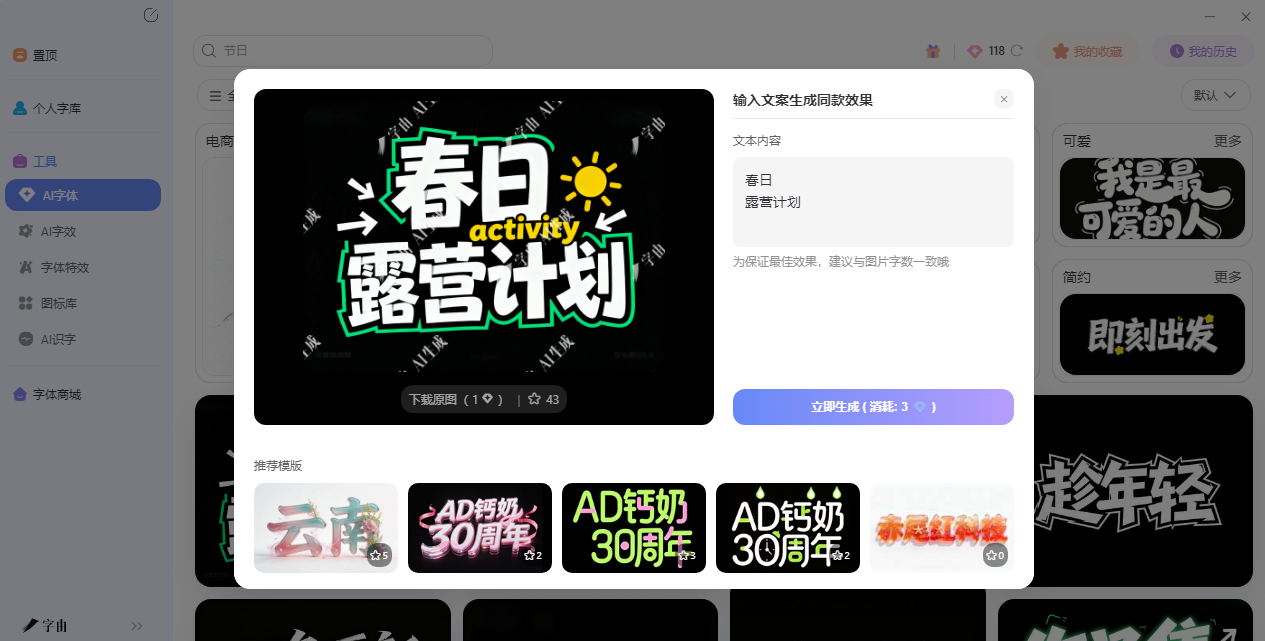
在线艺术字转换器,不用PS也能做标题
做海报封面、发社交媒体配图、设计 Logo 标题的时候,你是不是也想过:要是能有一款工具,输入文字就能直接变成艺术字,不用打开 PS 调半天图层样式就好了?现在网上有不少这样的艺术字转换器,输入文字选个模板或者样式,几秒钟就能出效果。今天整理了 5 个不同方向的转换工具,从 AI 一键生成艺术字图片,到复制粘贴的花体字,再到形状填充和 ASCII 字符画,覆盖了各种玩法,感兴趣的话就往下接着看吧!
字由是目前国内设计师用得最多的字体管理与 AI 字体平台之一,它的 AI 字体功能本质上就是一个艺术字转换器——不需要你懂设计,选个模板改几个字就能出图。
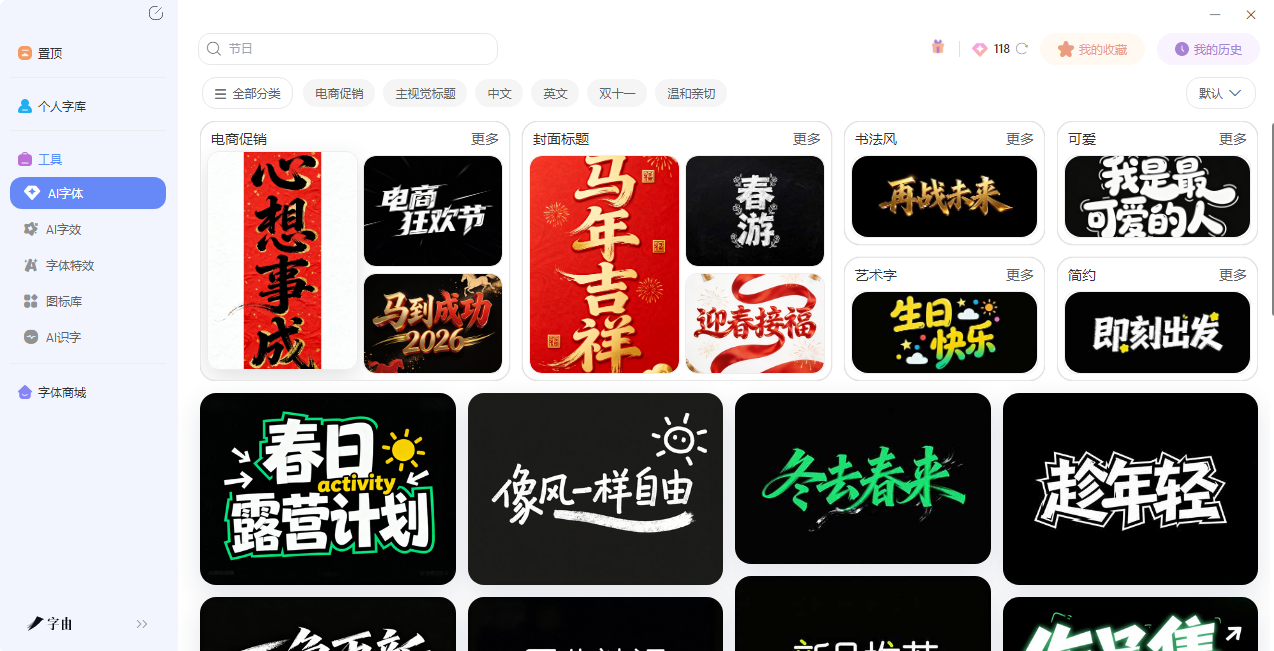
打开字由客户端,在“AI 工具”里找到 AI 字体入口。里面有多种字体特效模板。具体操作也很简单,很容易上手:首选可以根据自己的需求先筛选场景(比如要做电商促销海报,就选“电商促销”分类),找到喜欢的模板点“做同款”,在右侧输入自己的文案,点“立即生成”,等待 10 秒左右,系统就会生成一张带特效的艺术字图片。
生成后可以下载 PNG 格式,背景默认透明,直接拖进 PS、Canva、剪映里就能用。字由每天登录会赠送免费算力,日常生成完全够用。如果你做海报、封面、Banner 时经常卡在“标题字和海报画面不符”这一步,字由的 AI 字体比手动调参数快太多了。
2、Font Generator
第二个网站是一个 Font Generator,截图显示它提供了 200 多种独特的字体样式,主打“生成后复制粘贴”的使用方式。输入文字后,系统会生成各种花体、粗体、斜体、哥特体、气泡体等样式,每种样式旁边都有一个复制按钮。复制后的文字可以直接粘贴到 Instagram、TikTok、Roblox、微信等任何支持文本输入的地方。这个工具还提供了移动端 App(iOS 和 Android),方便在手机上直接生成花体字。
和生成图片的工具不同,这类生成器输出的是 Unicode 字符,所以不挑平台,任何设备都能正常显示。如果你只是想发一条花体字朋友圈,或者给游戏昵称加点个性,这个 Font Generator 比打开 PS 做图方便太多。
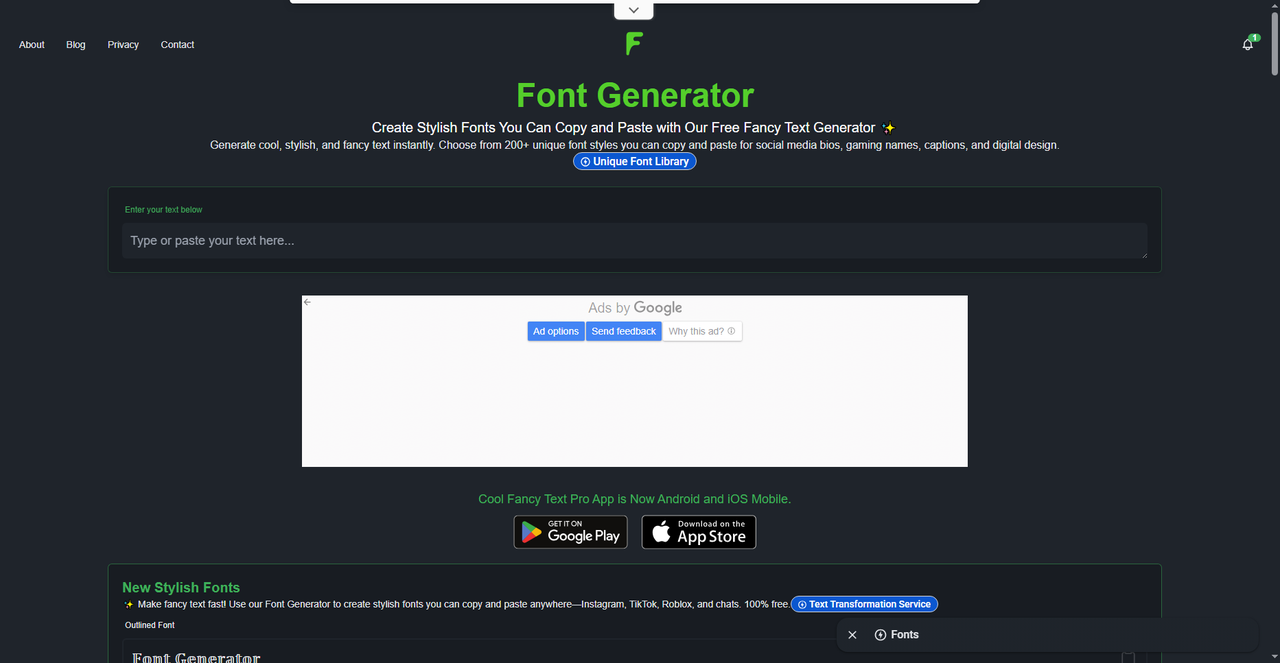
3、在线艺术字生成器
第三个是一个中文的在线艺术字生成器。它的特点是支持丰富的参数调节:可以选字体(比如“凉如三月”这种艺术字体),调文字颜色、背景颜色、字体大小、旋转角度、图片尺寸、字体投影、边距等。输入文字后,点击“生成”就能看到预览效果,然后下载图片。这个工具适合那些“对花体字不满意,想要更自由控制”的用户——你可以自己搭配颜色和背景,让艺术字更贴合海报的整体风格。相比纯花体字生成器,它多了一些设计自由度,又比 PS 简单很多。如果你需要的不是简单的 Unicode 花体字,而是一张真正可以放在海报里的艺术字图片,这个生成器值得一试。
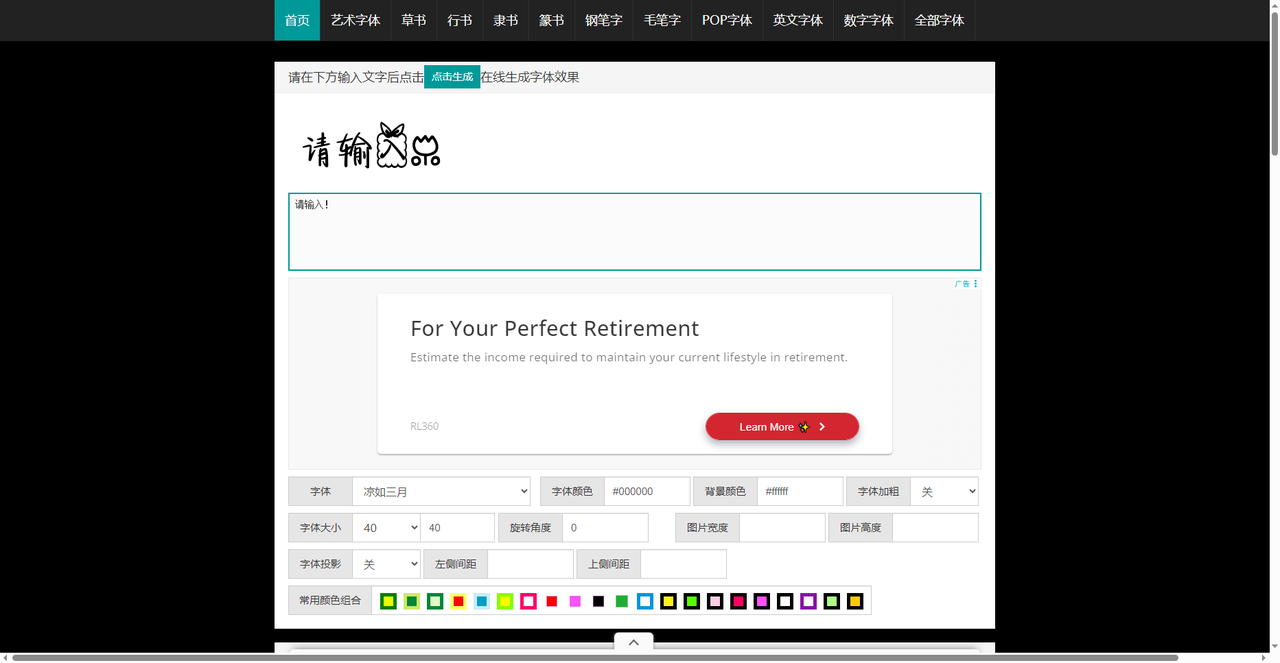
4、Wordificator
第四个工具叫 Wordificator,一个创意形状文字艺术生成器。它的玩法很特别:你选择一个形状(心形、圆形、动物轮廓等,也可以上传自己的图片),然后输入一组文字,系统会把文字按照形状的轮廓排列填充,生成一张形状文字海报。截图里展示的是心形填充效果,文字有不同的大小层级——用 * 开头的行会变成“Featured”(突出显示的大字),其他行作为小字填充周围。你还可以设置字体、颜色方案、背景色、字体大小等参数。生成后可以导出 2048×2048 的 PNG 图片。Wordificator 适合做活动海报、T 恤图案、社交媒体封面等需要“把文字排成特定形状”的场景。比如你要做一张“LOVE”主题的情人节海报,用 Wordificator 选心形,输入 LOVE、SMILE、BE HAPPY 等词,几秒钟就能生成一张有设计感的文字海报。
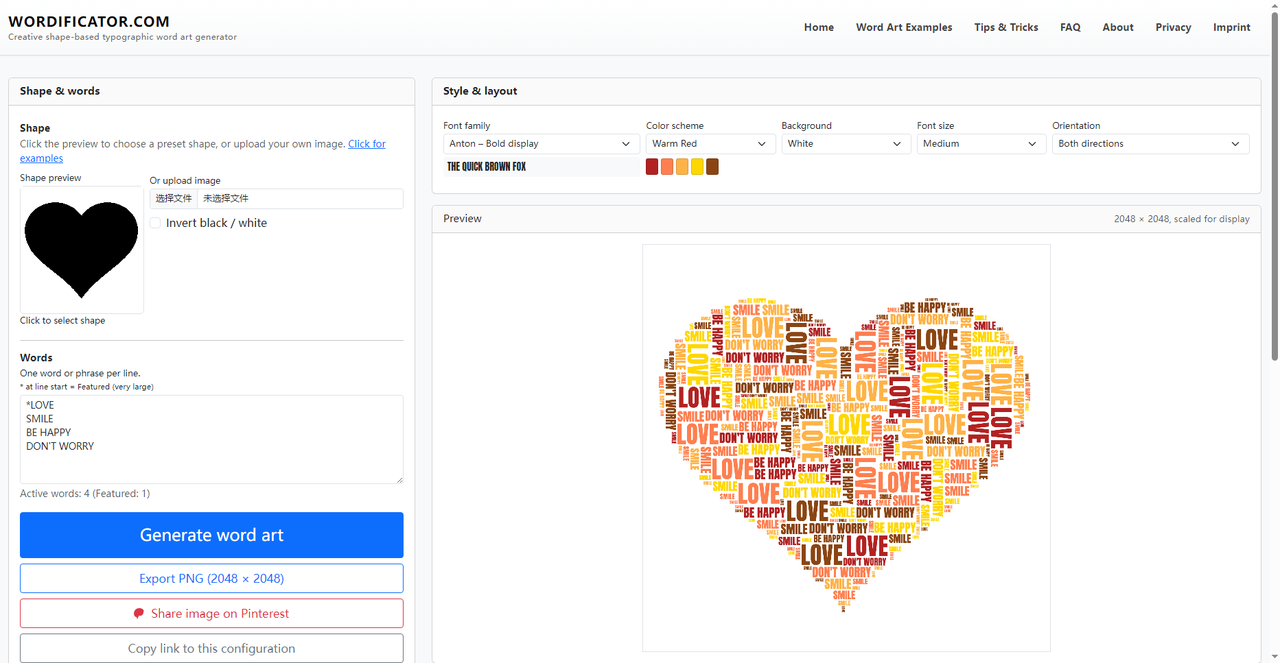
5、ASCII Art Archive
第五个工具是 ASCII Art Archive,一个专门做 ASCII 艺术的在线转换器。ASCII 艺术就是用键盘上的字母、数字、符号拼出图案或文字的一种艺术形式。这个工具提供了 270 多种字体样式,支持水平布局和垂直布局,可以调整宽度、边框、内边距等参数。输入文字后,它会生成由字符组成的艺术字,比如把“Hello World”变成用 # @ % 等符号拼出的大字标题。生成的结果可以复制成纯文本,粘贴到代码注释、论坛签名、邮件、聊天室等地方。ASCII 艺术有一种复古的极客美感,适合用在技术博客、程序员社区、复古风格的设计项目里。如果你想要一种完全不一样的艺术字风格,ASCII Art Archive 是一个很有趣的选择。